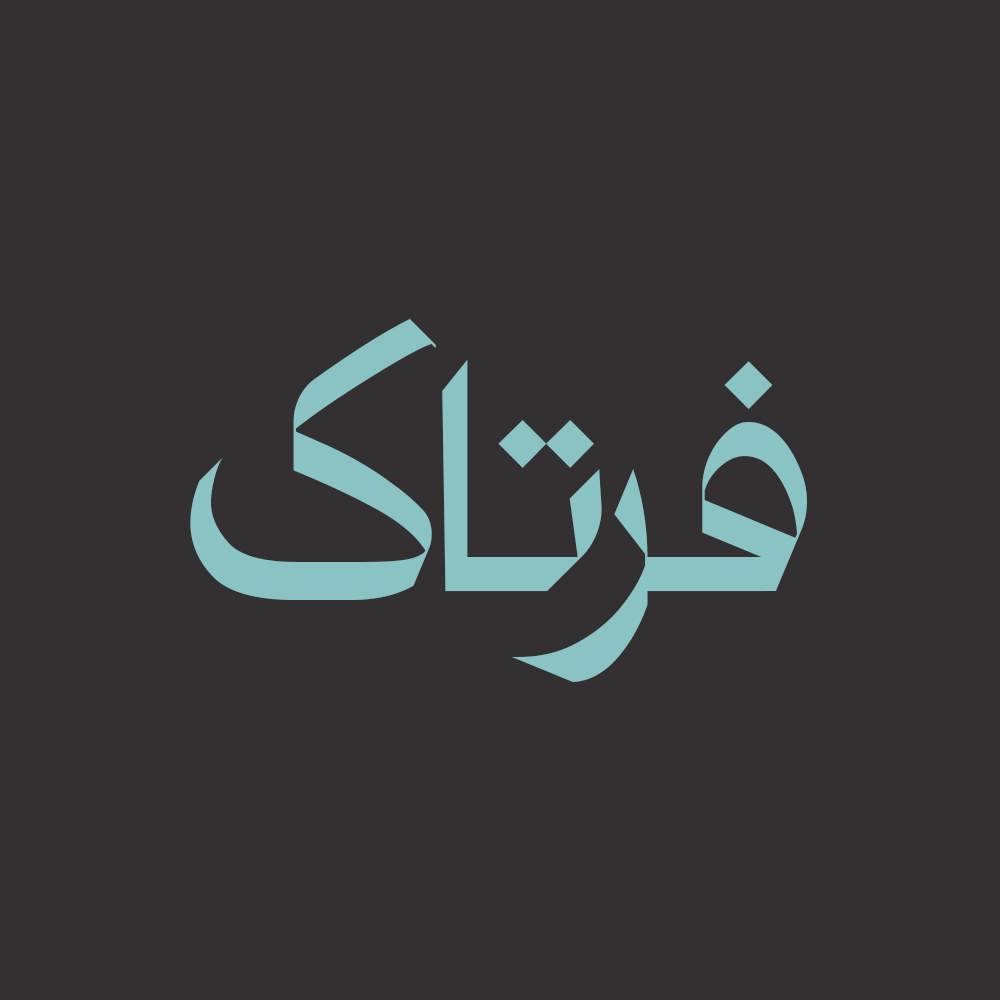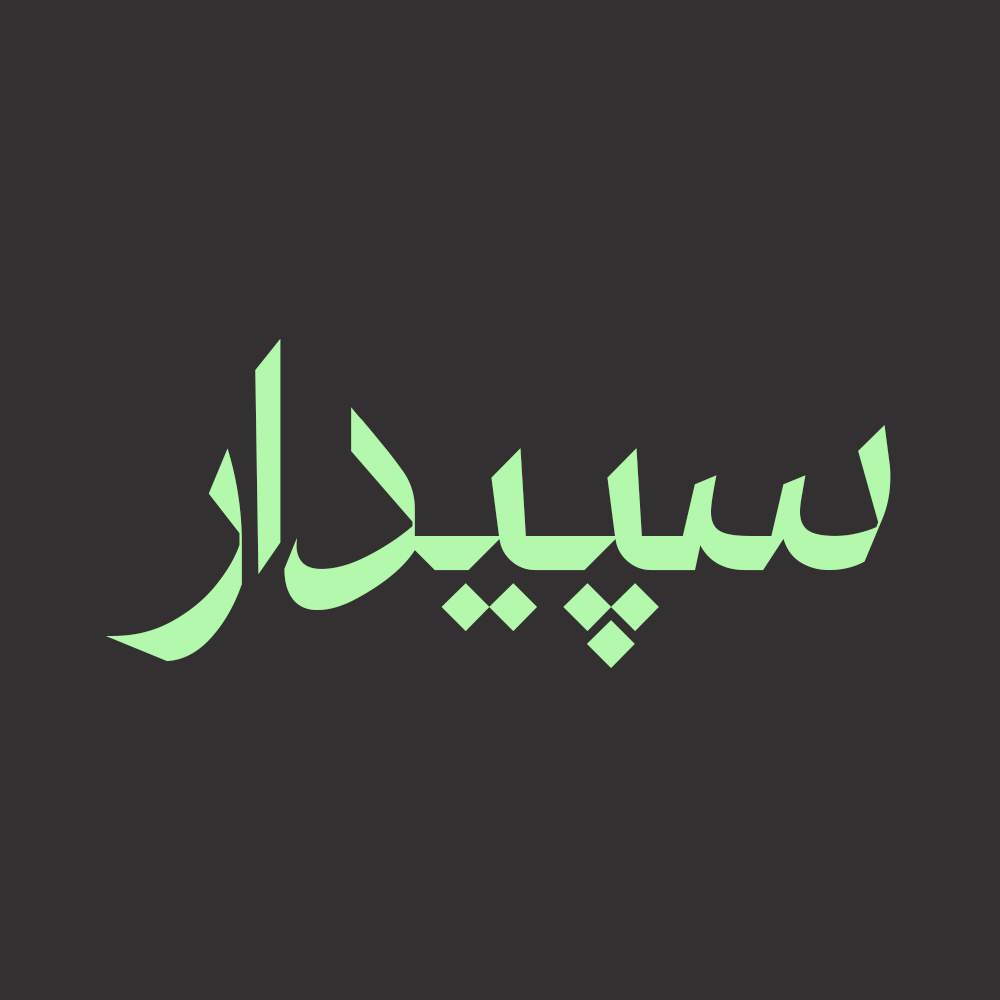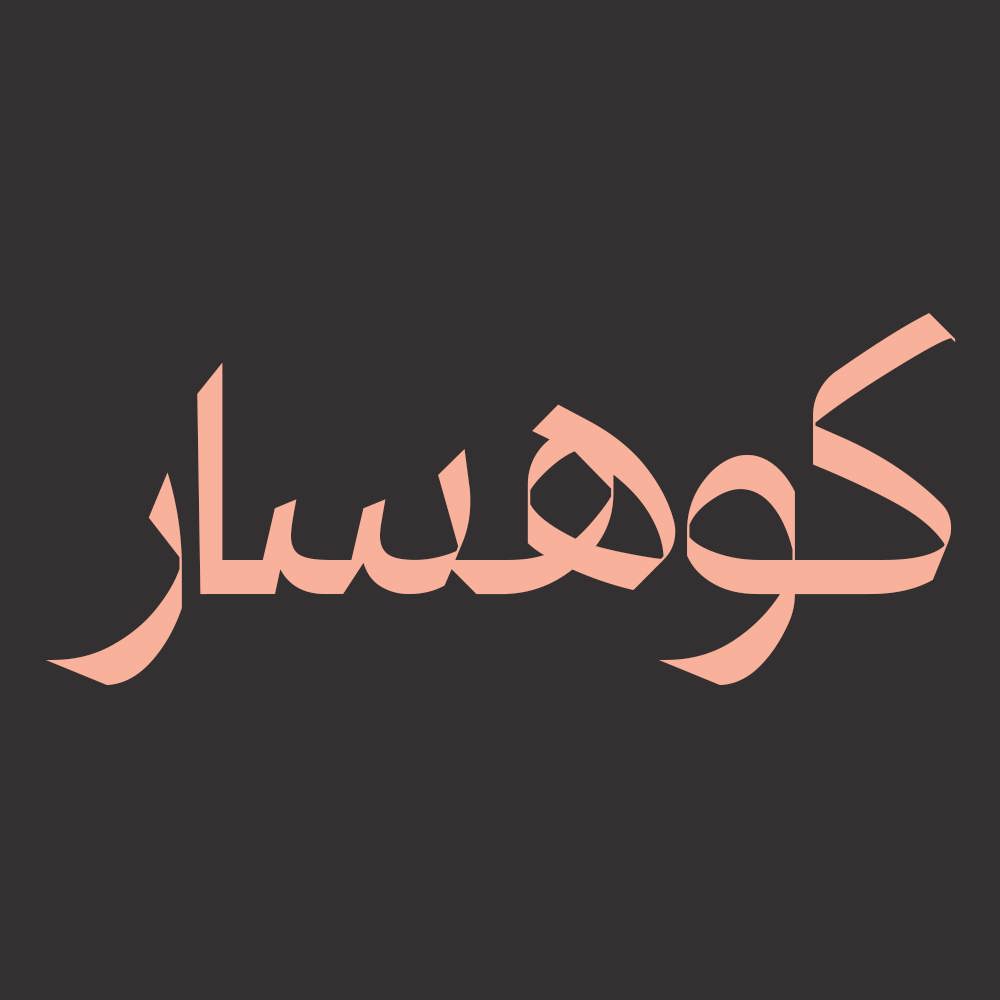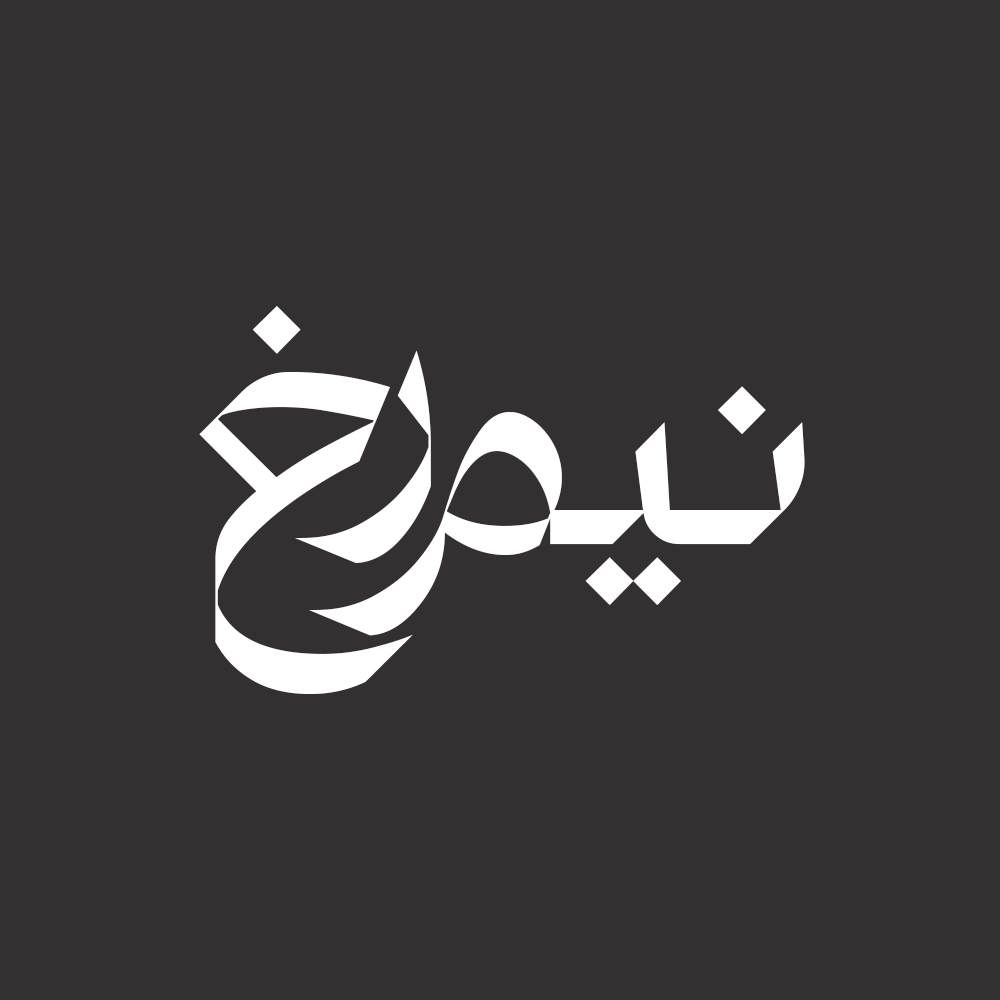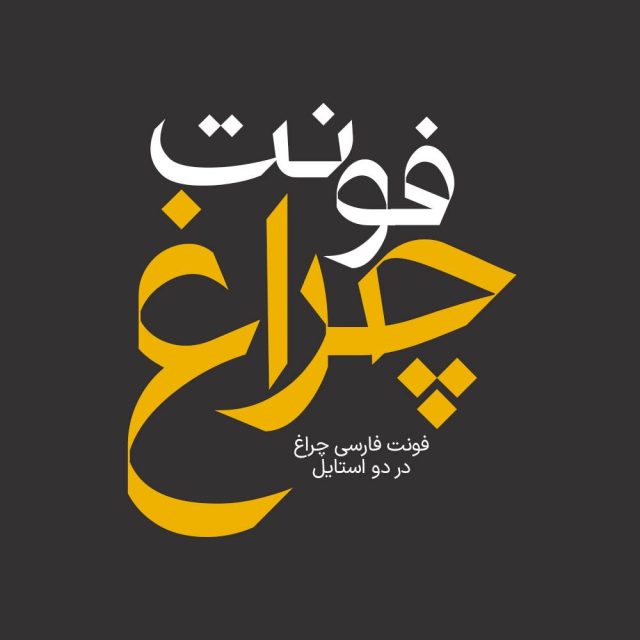
فونت فارسی چراغ Cheragh Font
اگر به دنبال فونتی خاص، مدرن و در عین حال ریشهدار در فرهنگ نوشتاری فارسی هستید، فونت فارسی چراغ انتخابی بینظیر برای شماست. این فونت در دو سبک با ترکیبی از خلاقیت بصری و اصالت طراحی ایرانی، مناسب پروژههای گرافیکی، طراحی پوستر، لوگوتایپ، بنرهای تبلیغاتی، تیتر مجله و حتی رابط کاربری اپلیکیشنها است.
خوانایی بالای فونت چراغ به سبب رعایت جزئیات و زوایای داخلی و خارجی سطوح فونت لوگو فارسی در نوع خود بی نظیر می باشد. پس می توانید از فونت چراغ در جهت خلق متن های های زیبا و جذاب استفاده نمائید.
فونت چراغ یک فونت تک وزن بولد با کاربرد طراحی لوگوتایپ و طراحی های مختلف همچون کتاب و تولید محتوای متن های کوتاه و عناوین می باشد. این فونت با فرمهای سخت و نرم خود مناسب استفاده در لوگوهای نوشتاری می باشد. همچنین از این فونت در طراحی تابلوهای چلنیوم هم به دلیل ساختار منحصر به فردش می توانید استفاده کنید. در ادامه برای شما نمونه تایپ های این محصول حرفه ای رو آماده کردیم که میتونید مشاهده کنید.
پیشنمایش و نمونه تایپ های فونت چراغ